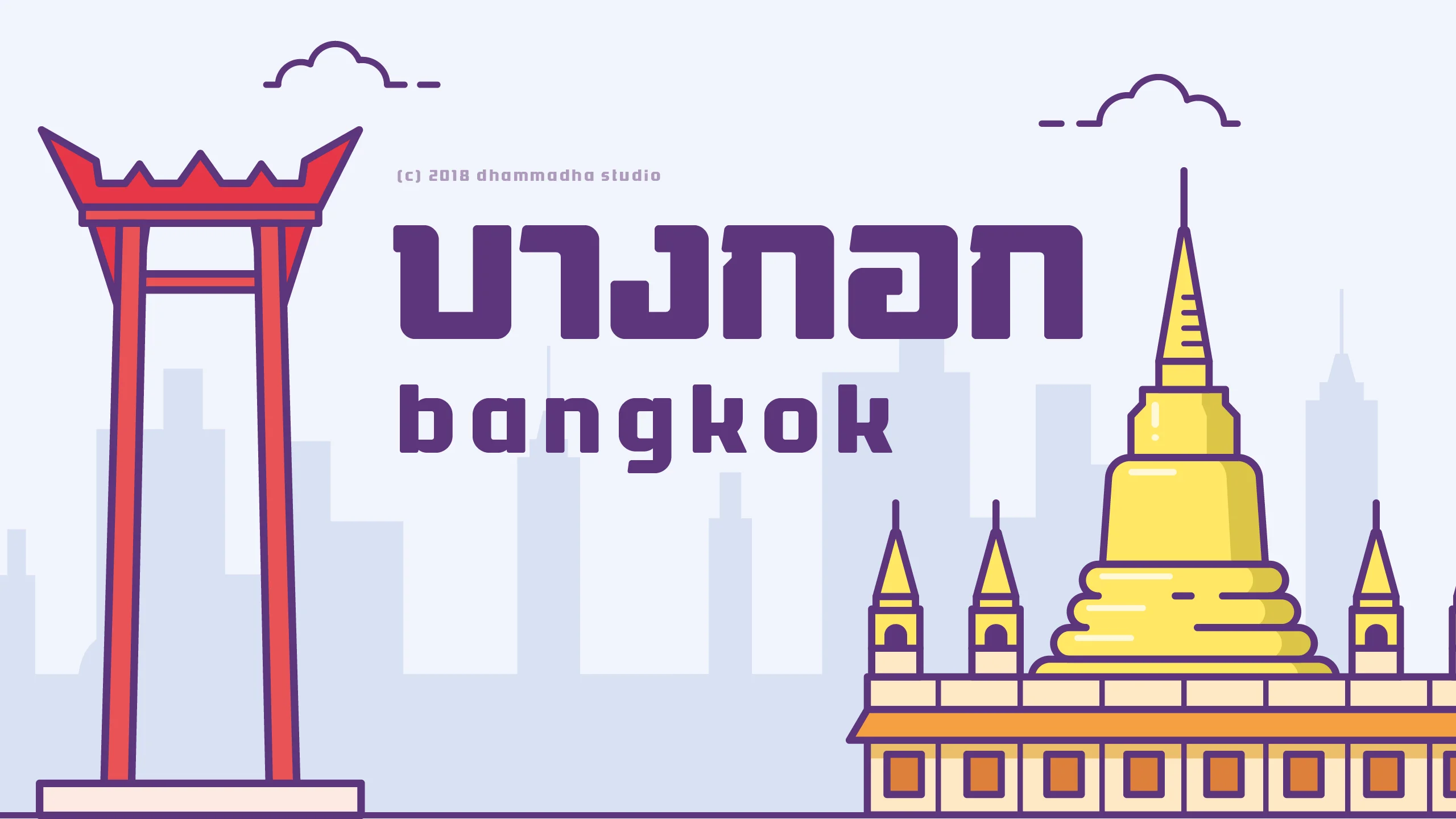
"บางกอก | bangkok" คือชุดอักษรที่ได้รับแรงบันดาลใจมาจากเสน่ห์ของ Logotype สุดคลาสสิกที่คนไทยคุ้นเคย โดยนำมาตีความใหม่ผ่านมุมมองที่เน้นความเป็นมิตรและเข้าถึงง่ายยิ่งขึ้น เราลดทอนความแข็งกระด้างลงและเติมเต็มความชอบส่วนตัวที่เน้นความร่วมสมัยเข้าไปเพียงเล็กน้อย เพื่อให้ได้ตัวอักษรที่มีรูปร่างแข็งแรง มั่นคง แต่กลับให้ความรู้สึกที่เป็นกันเองอย่างประหลาด สะท้อนบรรยากาศวินเทจที่ดูอบอุ่นและเปี่ยมด้วยเรื่องราวในวันวาน ด้วยโครงสร้างที่ดูภูมิฐานแต่แฝงไว้ด้วยความนุ่มนวล ฟอนต์ชุดนี้จึงเหมาะอย่างยิ่งสำหรับงานออกแบบที่ต้องการสร้างบรรยากาศที่ดูจริงใจและมีชีวิตชีวา ไม่ว่าจะเป็นงานสร้างแบรนด์ร้านอาหารสไตล์ย้อนยุค หรือการจัดวางตัวอักษรบนผลิตภัณฑ์ที่เน้นความเรียบง่ายแต่สะดุดตา "บางกอก | bangkok" จะช่วยเปลี่ยนให้งานดีไซน์ของคุณดูมีความเป็นมนุษย์และเข้าถึงใจผู้คนได้ง่ายขึ้น ในขณะที่ยังคงความโดดเด่นแข็งแรงไว้อย่างลงตัว